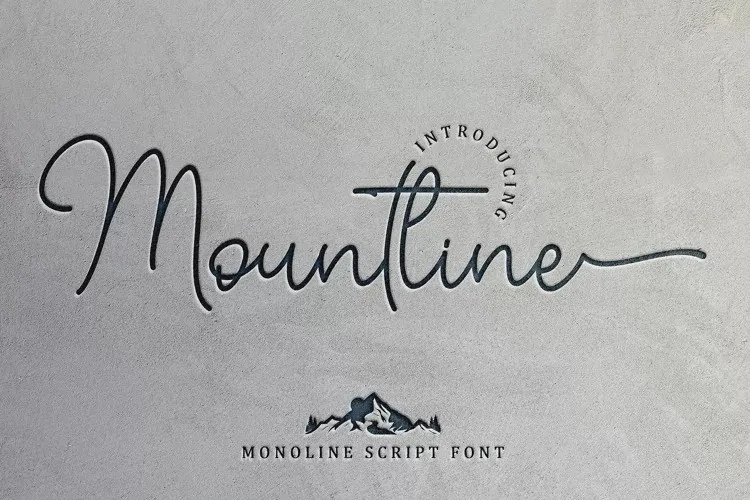
Mountline Font – Download Grátis
A “Mountline Font” é uma deliciosa mistura de letra escrita a mão que transmite uma sensação de elegância e serenidade. Desenvolvida por Sakha Design, esta fonte criada especialmente para scripts oferece letras distintas e bem equilibradas, tornando-a um verdadeiro marco na área do design tipográfico. O fato de estar PUA encoded permite uma facilidade impressionante ao acessar todos os belos glyphes e swashes desta fonte. É perfeita para designers que desejam enriquecer seus projetos com um toque elegante e único.